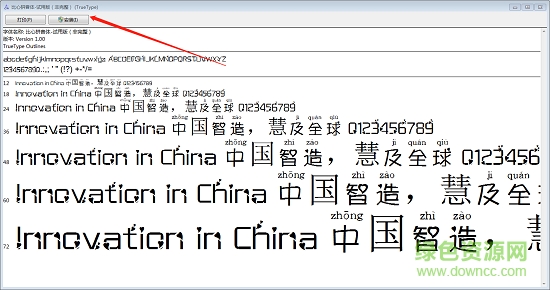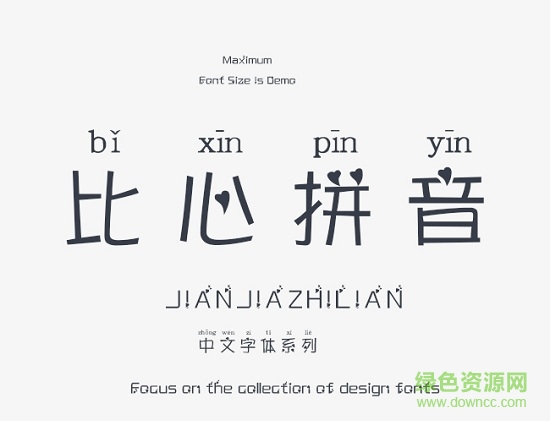
義啟比心拼音字體
義啟比心拼音體簡介:
義啟比心拼音字體是義啟字庫設(shè)計的一款非常具有愛心的字體,目的就可以可以讓你大膽的向你所愛的人表白,文字里所有的點都用心來代替,如果有英文的話,有些地方也被愛心點綴了,至于字形方面,有手寫風(fēng)格,一筆一劃,還算規(guī)整,給人的感覺比較寬!
義啟比心拼音字體
義啟比心拼音體特色:
1、逗號也變成了愛心;
2、字形方正、整齊,辨識度高;
3、視感較寬,重心偏上,彰顯個性;
4、文字的筆畫里沒有點,都是愛心;